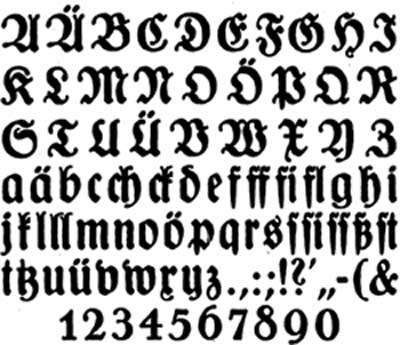
Fraktur der früheren Neuen Osnabrücker Zeitung gesucht
darum erst jetzt die notwendige Ergänzung zur gesuchten »Block-Fraktur«:
Froescher entwarf auch eine magere und halbfette Version. Berthold
veröffentlichte diese 1915/16 allerdings unter dem Namen »Stuttgarter Fraktur«.